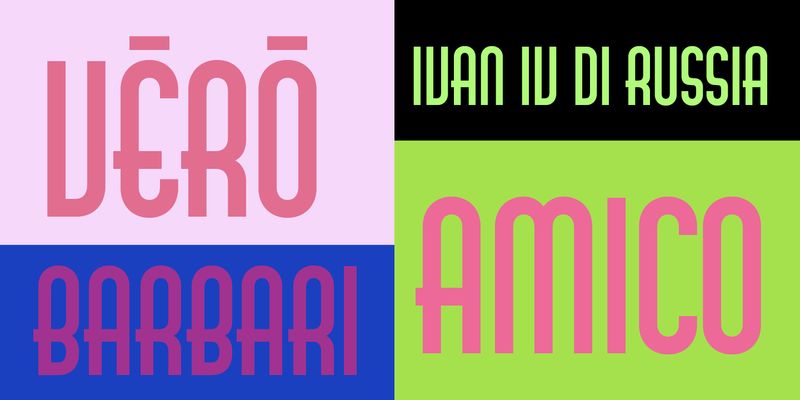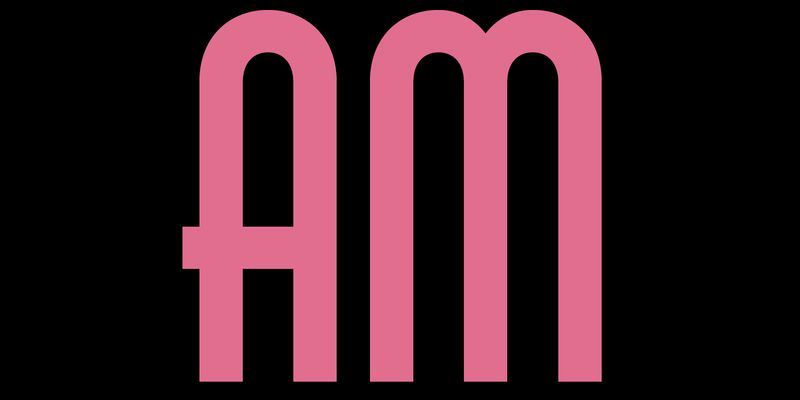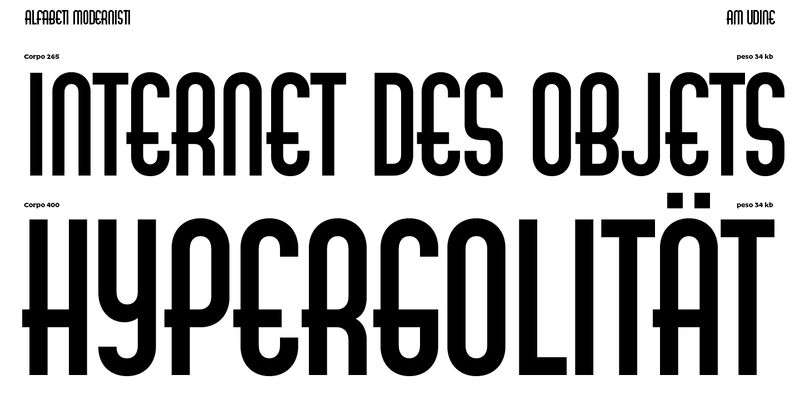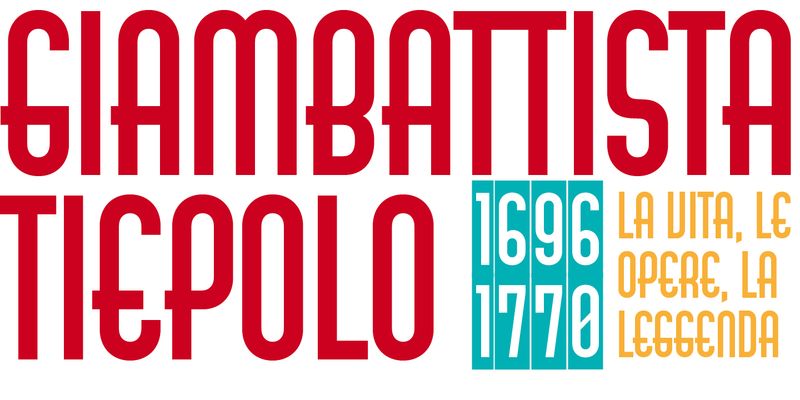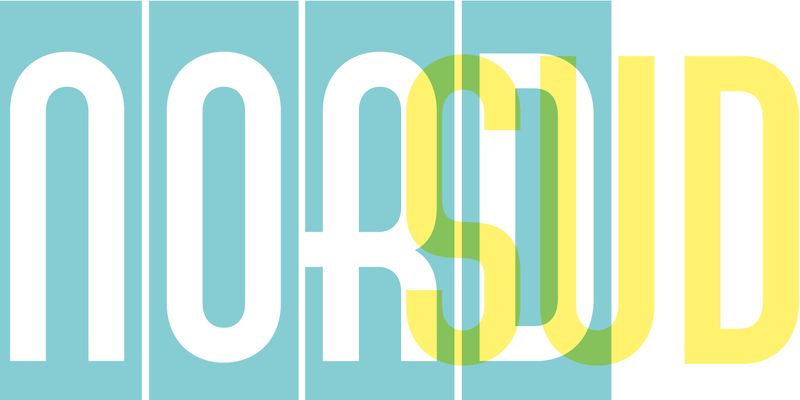
Udine はオールキャップスのモジュール式のサンセリフ体で、その狭いプロポーションと幾何学的なシェイプにアールデコの影響がはっきりと表れています。この書体デザインは、Nebiolo の最も象徴的な書体の 1 つである Neon と非常によく似ています。実際、同じ会社で作成されていなければ、盗作と見なされるほど似ています。
Udine は、トリノの Nebiolo 社によって木版活字として作成されました。1933 年のカタログに初めて登場したのは、8 行から 40 行 (およそ 100 ポイントから 500 ポイント) の 5 つのサイズでした。H と O の文字は、アルファベット全体を構成する基本的なモジュール式のシェイプです。ほぼすべての文字の幅は同じで、カウンターによって予測可能な規則的なパターンが作成されます。A、B、E、G、H、K、P、R などのいくつかの文字には、左に伸びる水平のストロークが表示されます。この特徴に加え、中央のストロークを持つすべての文字の重心が低いことは、アールデコの表現の一部です。
Neon との類似性は非常に顕著であるため、Udine はモジュール式書体の最初の試みであり、さらに開発された後、Neon ファミリーになったと考えられます。Giulio Da Milano と Alessandro Butti は、前者はアートディレクター、後者は製図技師であり、この書体のデザイナーであることは間違いありません (ただし、制作用のパターン描画の準備に対する Butti の貢献を軽視することは、おそらく彼の功績を軽視することになるでしょう)。第二次世界大戦後、木版活字 Neon の制作により Udine は不要になり、Nebiolo のカタログから姿を消しました。
デザイナーの Michele Patanè は次のように述べています。「AM Udine のデジタル復刻版は、オリジナルを非常に正確に反映しています。いくつかのディテールはデジタル環境で最適なパフォーマンスを発揮するように改訂されました。まず、オリジナルモデルの特徴的なモノリニアストロークは、水平ストロークを数単位減らすことで微調整されています。次に、曲線、および曲線と直線の間の遷移にわずかな調整が加えられ、書体のモジュール式のスタイルも、基本的な幾何学的シェイプを貼り合わせたような印象を避けるために慎重に作成されています。これらすべてにより、画面上で文字を見たときに感じられる不均一さが補正され、オリジナル書体の個性の一部であるアナログな硬さの感覚が維持されています。」
オリジナルの Udine は、各文字が黒い長方形に配置され、1 語または数語のタイトルの最初と最後に装飾ピースを配置するネガバージョンとともに提供されました。これらの機能は、OpenType 機能を通じて AM Udine デジタル復刻版で利用できます。